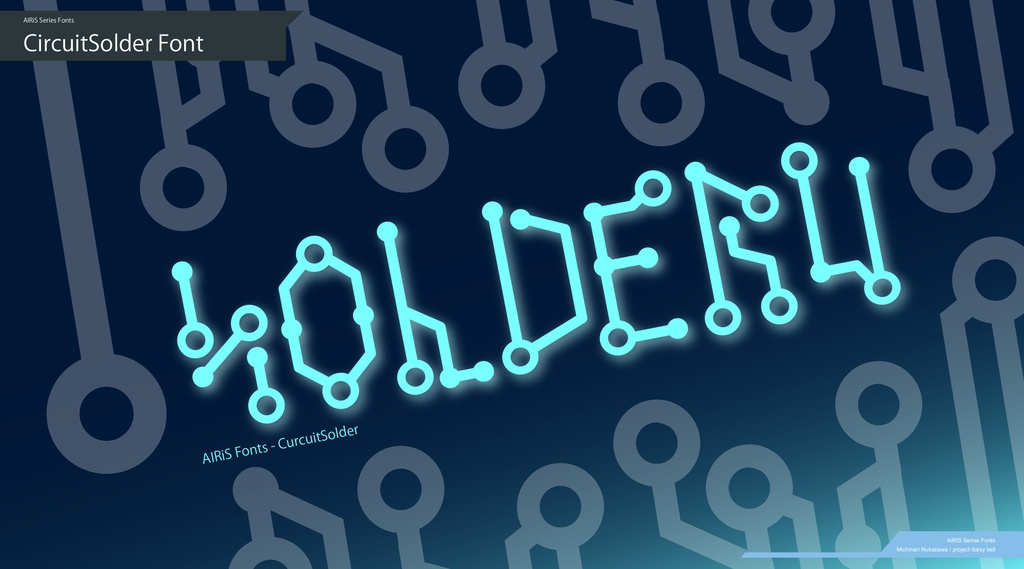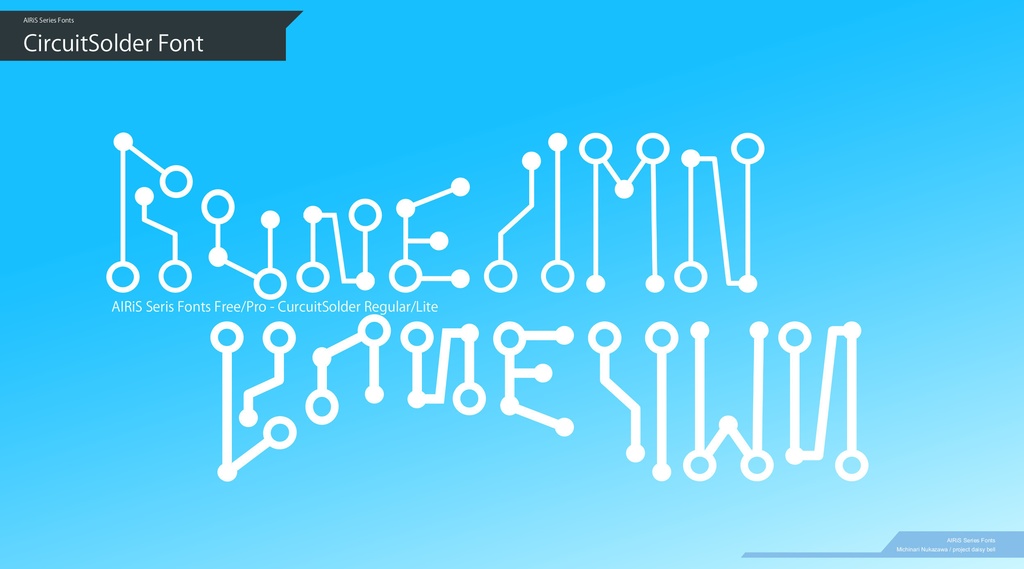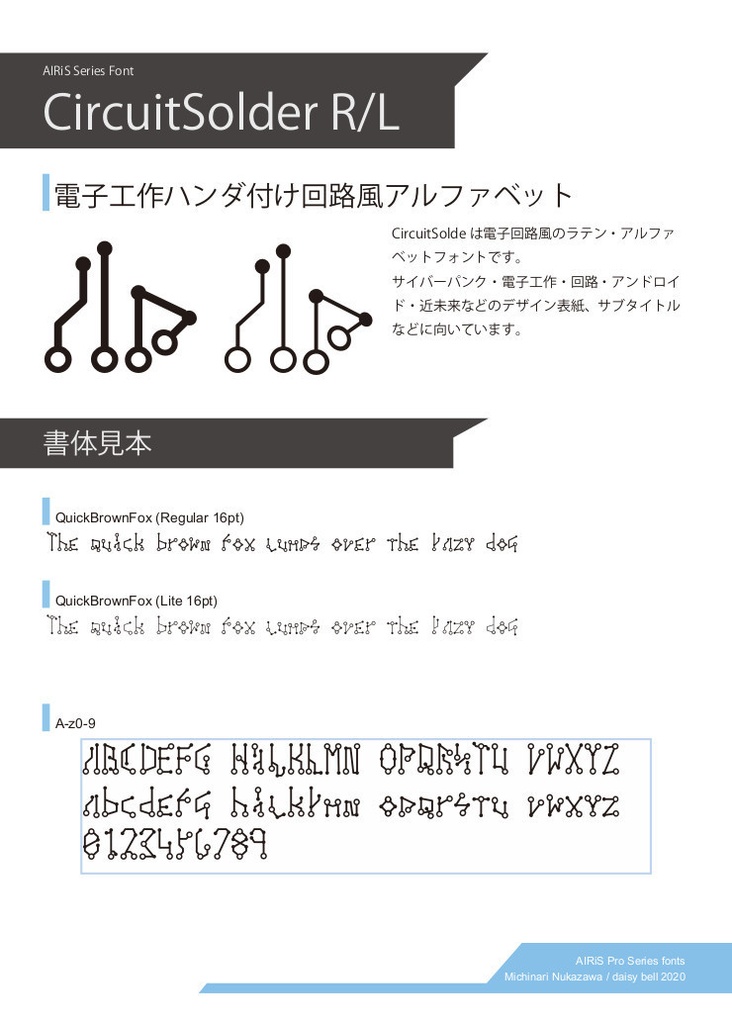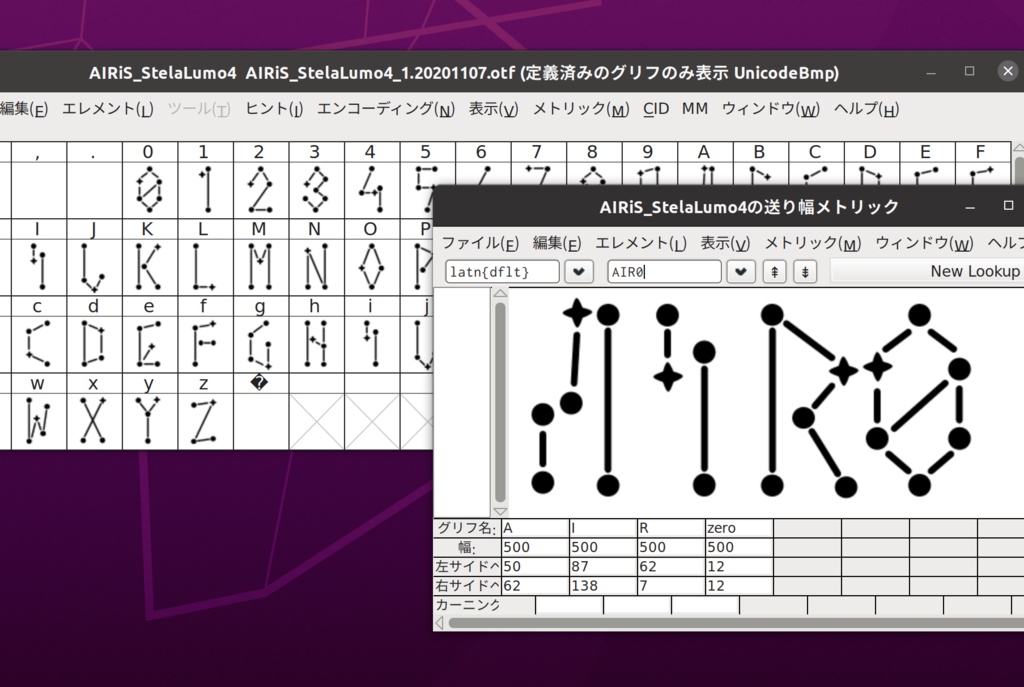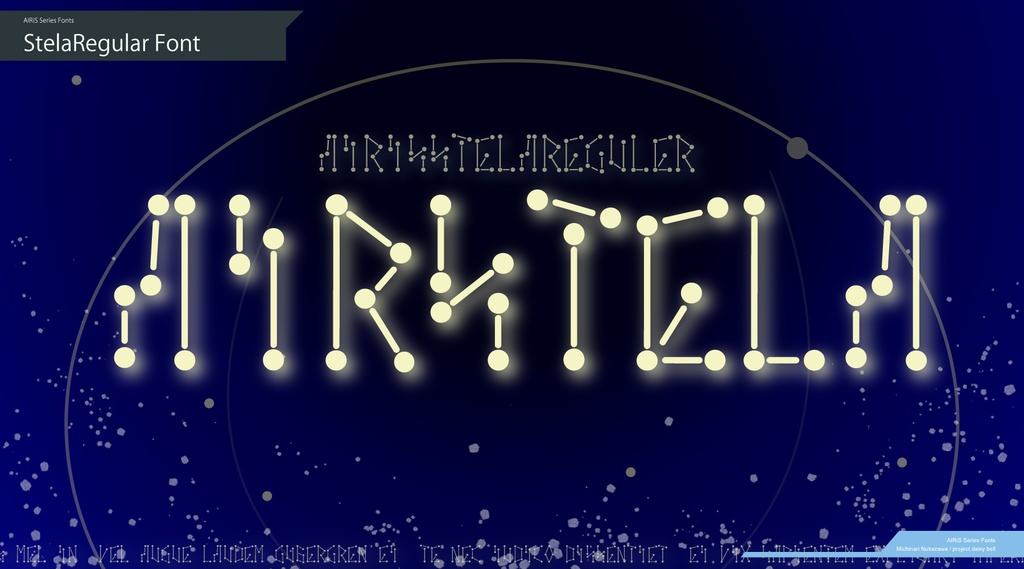
AIRiS - 華美装飾フォント集 (商用版)
電子回路風ラテン・アルファベットのフォント セットです。 『理由なしの90日間返品保証』付き。 ラテン・アルファベットと数字(A-Z,a-z,0-9)を収録。 また一部カナ漢字あり。 (収録文字はフォント毎に異なりますのでご確認ください。) 収録書体は以下。 CircuitSolder*シリーズ: サイバーパンク・電子工作・回路・ロボット・アンドロイド・近未来などのデザイン表紙、サブタイトルなどに。 Stela*シリーズ: 宇宙・ロケット・星空・天体観測・星座占いなどのデザイン表紙、サブタイトルなどに。 BOOTHアカウントをお持ちでない場合、Gumroadでも購入可能です。 https://gumroad.com/l/oIxvw 商用可。 ライセンスはRuneAMNシリーズフォントに準じます。 https://github.com/MichinariNukazawa/RuneAMN_Pro_Series_Fonts/blob/gh-pages/docs/etcs/LICENSE.txt 大規模開発などで使用する場合は、専用のディスカウントライセンス等、別途お問い合わせください。 サポートはメールまたはtwitterにて行っています。 ご意見・ご感想も気軽にお寄せください。 mail: michinari.nukazawa@gmail.com twitter: https://twitter.com/MNukazawa